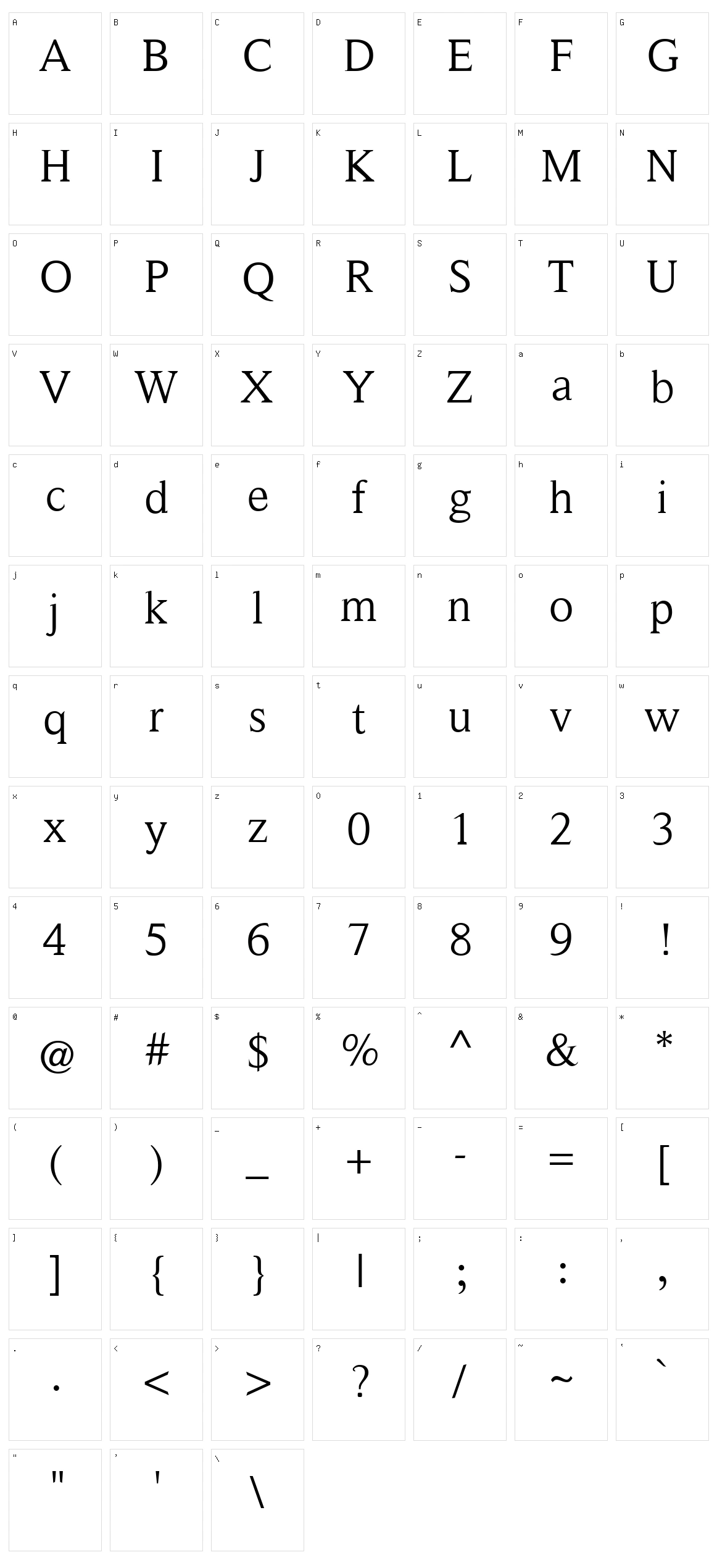
Il font si presenta come font serif dalle linee clssiche e minimali, grazie alla sua eleganza ed alle sue linee classiche è ottimo per la preparazione di stampe istituzionali e preparazione di grafiche per liberi professionisti ed attività per il business.